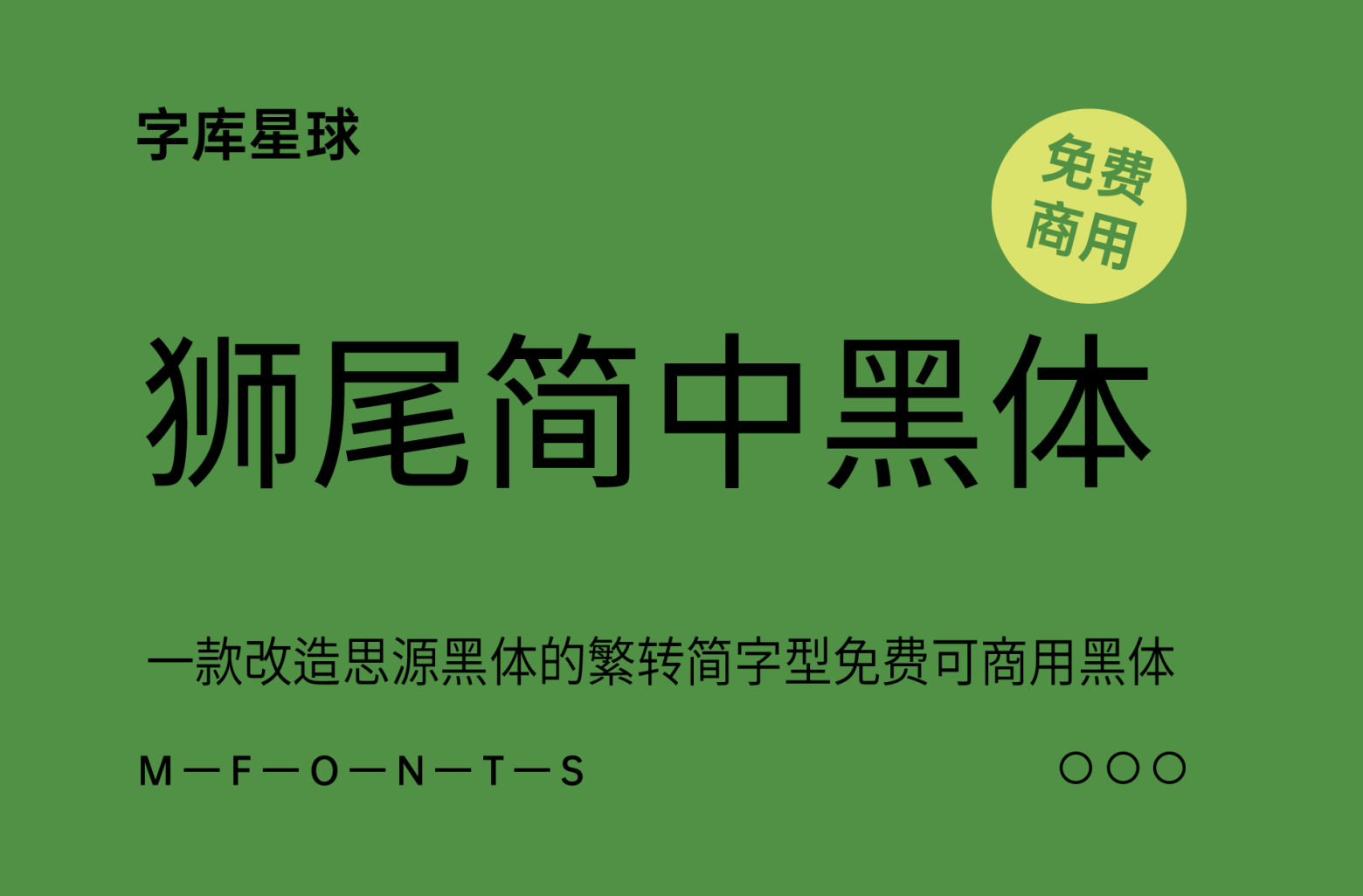
狮尾简中黑体
狮尾简中黑体基于思源黑体的繁转简字型;可以免费商用,欢迎大家自由应用、自由改作!
狮尾简中黑体的特色是:繁体字转成简体字的字型档,由于是转成简体,所以能处理「一简对多繁」。
「狮尾简中黑体」与「狮尾简腿黑体」差别在有没有拔脚,「拔脚」就是会有较少的笔画,例如移除「口」字的左右下角会多出的短线条。有拔脚的字会较圆,但是会造成有些字因直接去掉腿后左右不平衡、左右不对衬的「悬空」问题。改使用「腿」系列字体就不会有这个问题。
狮尾简中黑体
说明:繁中的「发」和「发」在简中都是「发」;繁中的「后」和「后」简中都是「后」。
「狮尾简中黑体」设计上针对笔画粗细支援7种字重,所以不论大标、小标、简单的段落排版都能清晰辨识。